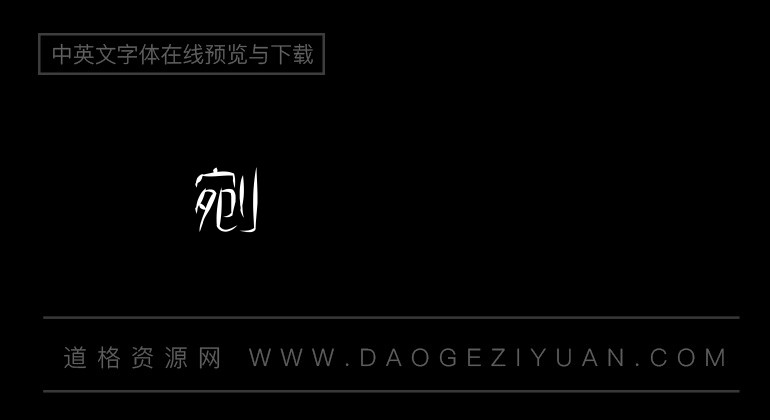
金梅落叶美工字体
金梅落叶美工字体是一款折衷风格的字体,具有清新、简约、温柔的设计风格,适合用于各种广告、婚礼、节日、活动、海报等设计中。它拥有独特的细节设计,可以让文字更加生动活泼,给人以温馨、柔和的感觉。它的字体特点是英文字母、数字以及符号都有独特的设计,让文字更加精致,更具有视觉冲击力,为您的设计带来更多的灵感。
金梅落叶美工字体是一款非常不错的手写艺术字体,具有很好的视觉感,适合于文化类的宣传设计、商业类品牌的广告和产品包装设计以及个性化文字排版等较多场景。